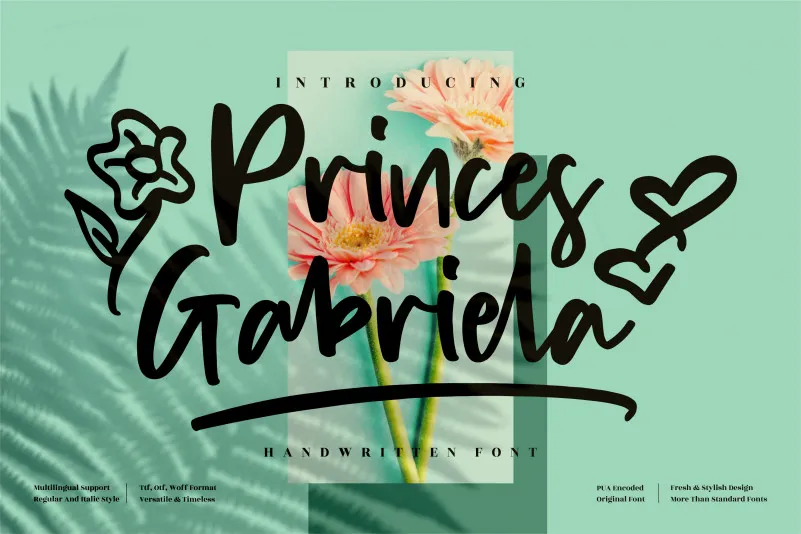
A ‘Princes Gabriela Font’ é uma criação perfeita para projetos que exigem personalidade única e charme elegante. Ela foi projetada com a mão, garantindo um toque de autenticidade que enriquece qualquer projeto. Seja em aplicações como logotipos, designs de marcas ou embalagens, revistas, materiais de presenteio e muito mais, essa fonte oferece o tom ideal para destacar seu trabalho. O design delicado desta fonte combina facilmente com diversos estilos e formatos, tornando-a uma opção versátil para designers que buscam adicionar um toque especial a seus projetos de criação de identidade visual ou editoriais. Com sua riqueza em detalhes e elegância simples, esta font é perfeita para aqueles buscando dar vida às suas ideias com uma escrita à mão autêntica, oferecendo o equilíbrio ideal entre sofisticação e criatividade.